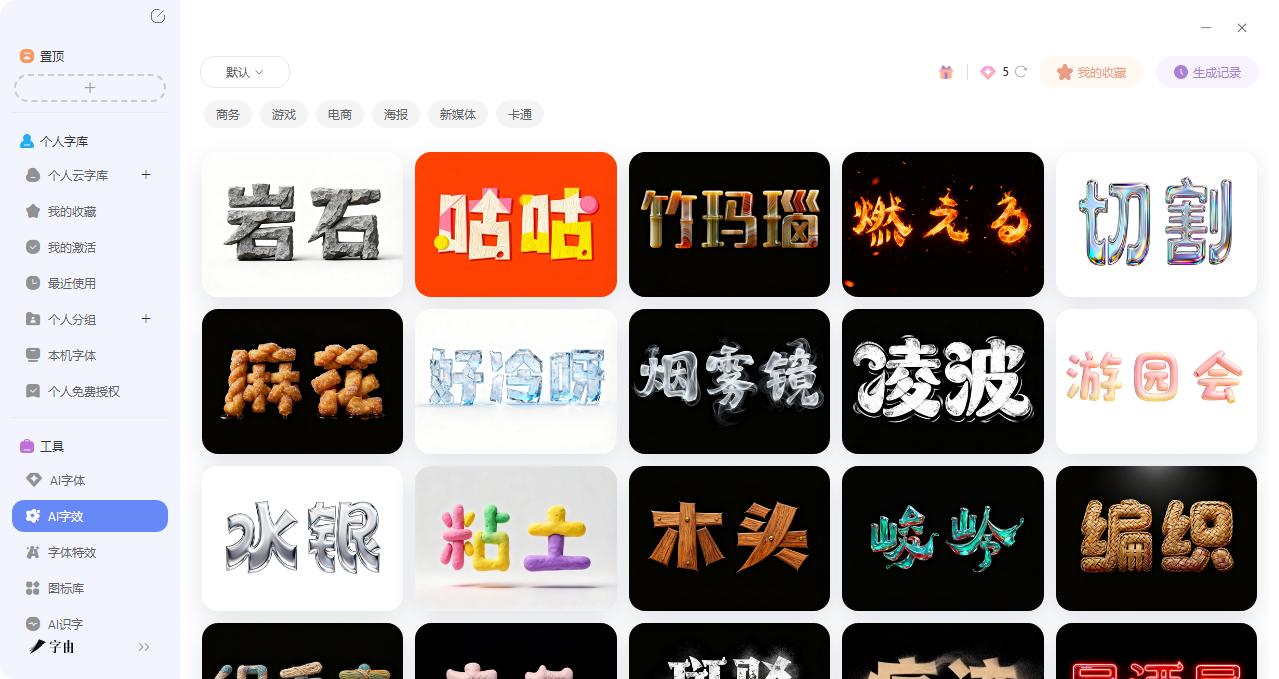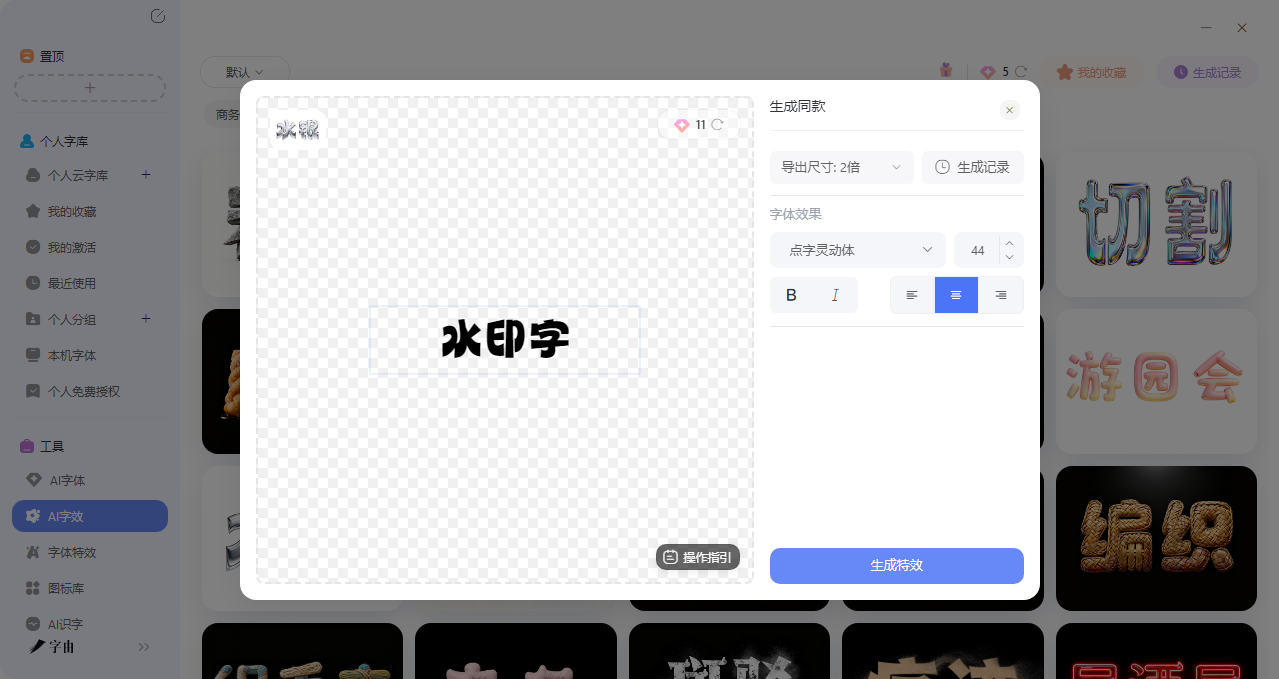
想要立体感标题?这5个自动生成工具别错过
不知道你有没有注意到一些交互感强的、引人注目的、新奇的封面往往会使用一些3D 字体,它们有厚度、有光影、有质感,仿佛要从屏幕上跳出来。这种立体字体以前可能要用PS慢慢调图层样式,或者用C4D 建模渲染,对新手来说门槛实在太高。但是现在不用担心了,今天我就筛选了5个亲测好用的立体艺术字自动生成工具,AI 工具可以让立体艺术字自动生成变得无比简单。每个都能帮你快速获得自带3D 质感的艺术字。需要的直接收藏!
首先要推荐的立体艺术字自动生成工具是字由。虽然大家熟知它可能是因为大量免费可商用的字体,但是它还有AI 字效这个非常实用的工具,专门用来生成各种风格的艺术字,其中就包括了大量的3D 立体感艺术字。
那么到底怎么生成呢?接下来我会教大家具体的制作步骤:
- 第一步:在字由客户端左侧导航栏点击【工具】→【AI字效】,或者从首页【字体工具】→【AI字效】进入。
- 第二步:在模板库里找到“3D立体”“质感字”“浮雕效果”等分类,或者搜索关键词“立体”“3D”“浮雕”。模板包括:
- 气泡3D字
- 金属质感立体字
- 浮雕石刻效果
- 霓虹发光立体字
- 积木堆叠效果
- 第三步:点击“做同款”,输入你的标题文案。
- 第四步:点击生成特效,等20-30秒就能得到高清立体艺术字图片。支持透明背景下载,直接拖进设计软件里用。
除了AI生成,字由本身的字体库里也有不少适合做立体效果的字体,比如:
- 字由文艺黑:既有黑体的稳重又带手写感,加立体效果后很有质感。
- 优设标题黑:方正有力,适合做粗重的立体标题。
- 字由源黑:厚实稳重的黑体,加厚度后视觉冲击力强。
在字由的“免费字体”里,选好基础字体后,再用AI 字体特效添加立体效果,相当于“字体+特效”两步搞定。
2、BYLO AI
BYLO AI 是一个功能强大的AI图像生成平台,它的3D文字生成功能非常专业。而且它是基于Google DeepMind的Nano Banana 模型,可以生成高度逼真的3D文字效果。这个网站的核心亮点就在于可以支持快速生成以及4K 分辨率,同时支持PNG、JPG、WEBP上传,单张最大5MB,可批量处理。当然,如果你想要更高需求的话,可能就要选择购买pro版本了。
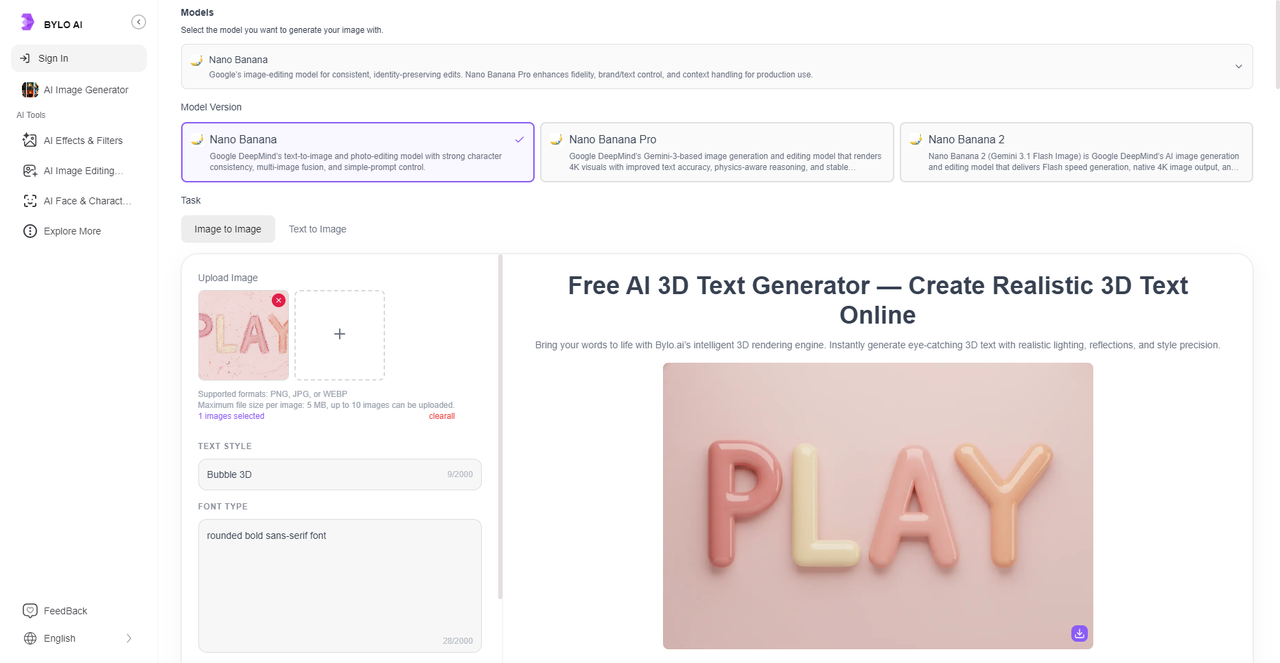
3、AI 3D Font Generator
这个网站的界面和操作要比上一款网站简便得多,主打快速生成立体艺术字,因为你可以看到它只有一个输入框和生成按钮,但效果很惊艳。具体的使用方法如下:
- 在输入框里写下你的需求,比如“Write '3D' in a realistic colorful 3D bubble letter font”(用逼真的彩色3D 气泡字体写“3D”)。
- 点击“Generate font”,AI就会自动生成立体艺术字。
这个网站就胜在操作简便、速度极快,适合需要快速出效果图、或者不确定想要什么风格先试试水的场景。
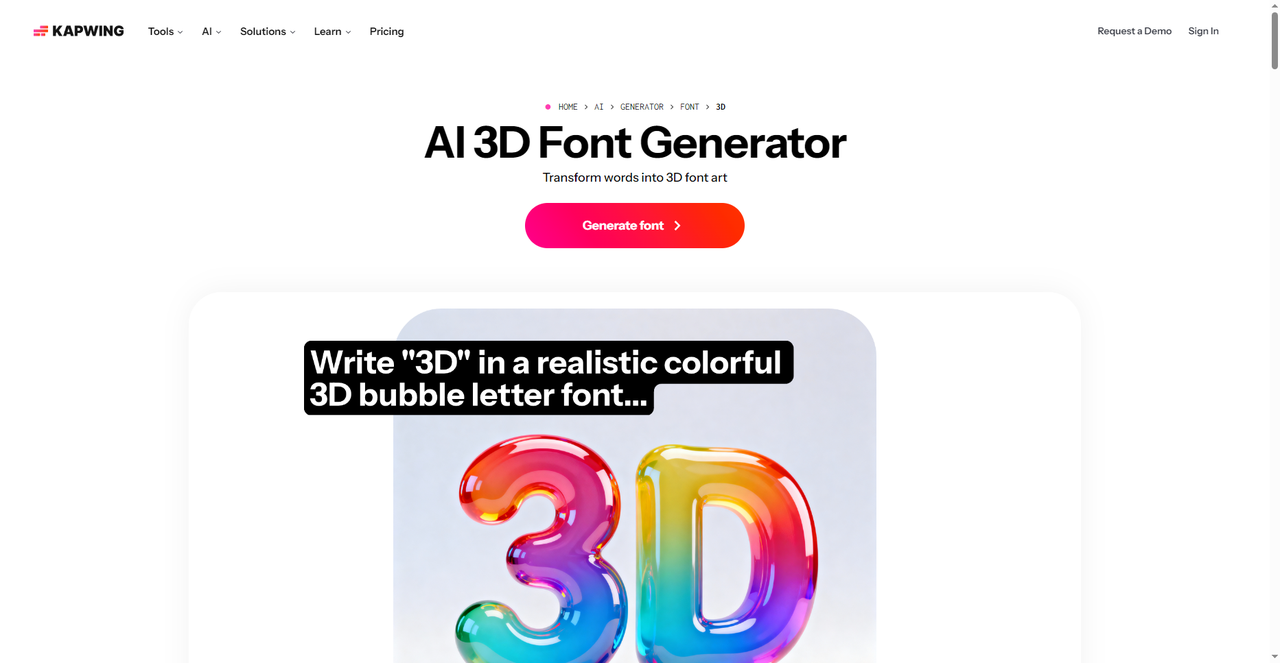
4、3D Text & Logo Maker
这个网站功能非常全面,尤其是针对3D 文字制作工具,可以在浏览器里直接创建立体文字或 Logo。我先来给大家介绍一下左边侧栏的功能模块:
- Text:输入文字(支持多行,Shift+Enter换行)。
- Typography:选择字体样式。
- Logo:上传Logo进行3D处理。
- Geometry:调整立体几何参数(厚度、角度等)。
- Material:选择材质(金属、塑料、玻璃等)。
- Environment:调整环境光照。
- Background:设置背景颜色或图片。
仅仅是这些内容你应该就可以看出这个网站有多么专业了,而且它还支持把SVG 矢量图一键转换为3D 模型,免费使用。这个工具相当于一个轻量级的3D建模软件,而且还不用下载任何软件,唯一的缺点可能就是使用的时候会有些卡顿了。
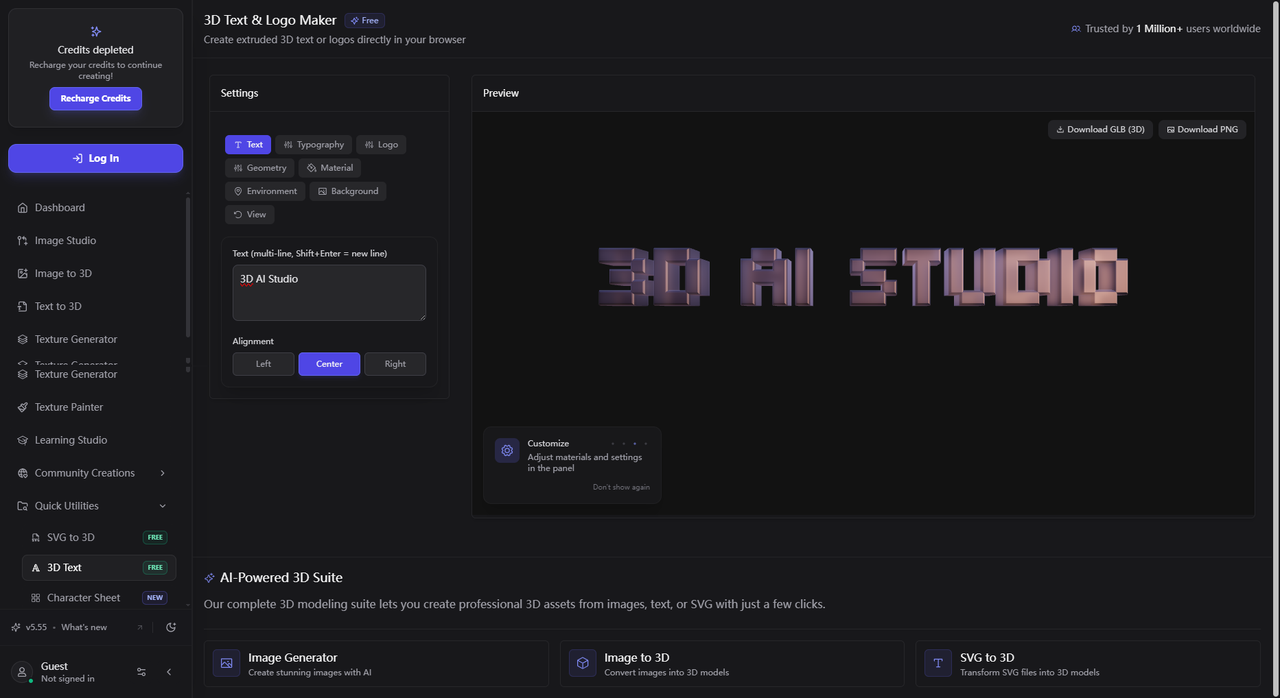
5、Fontly 3D Font Generator
这也是一款轻量级的3D 字体生成的在线工具,界面清爽,功能上手快。具体的使用方法大概可以分为以下几个步骤:
- 在输入框里输入文字(如“3DText”)。
- 工具会自动生成多个不同风格的立体文字效果预览。
- 点击喜欢的样式,可以进一步调整或下载。
这个网站就胜在特效字体款式特别多,截图只是展示的一小部分,原网站往下滑还有很多可供选择的特殊字体,其中就包括金属质感、浮雕效果、描边立体、光影投影等。每种风格都配有预览图,方便对比选择。这个工具的优势是“所见即所得”——输入文字后立刻看到多种效果,省去自己试错的时间。适合需要快速定稿的商业项目。
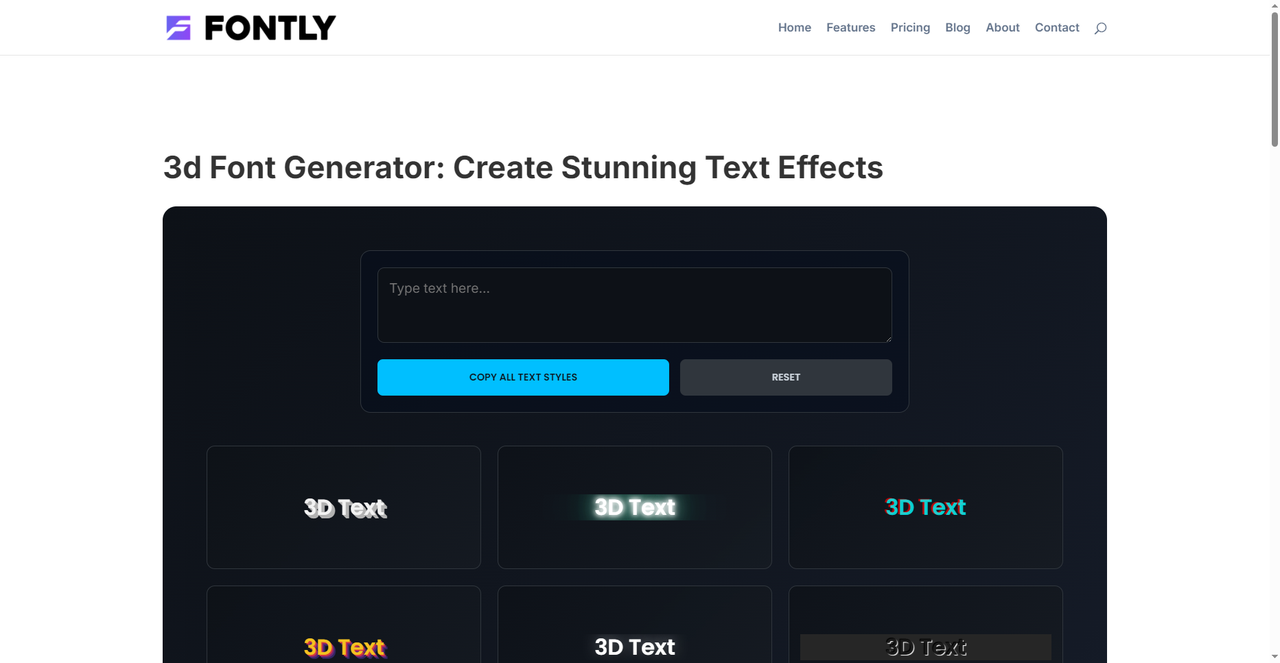
以上这5 个立体艺术字自动生成工具可以说覆盖了做设计各个层面的需求,3D Text & Logo Maker 功能全面,上手难度会有点高,比较适合想要高质量字体特效的设计师,Fontly 界面简洁,操作简便,比较适合新手。但是只有字由会让我觉得操作十分简便且产出高质量,它把字体库和AI特效放在一起,足够你慢慢挑选,还不用来回切换软件。如果你也想让标题真正“立”起来,不妨从字由开始试试。